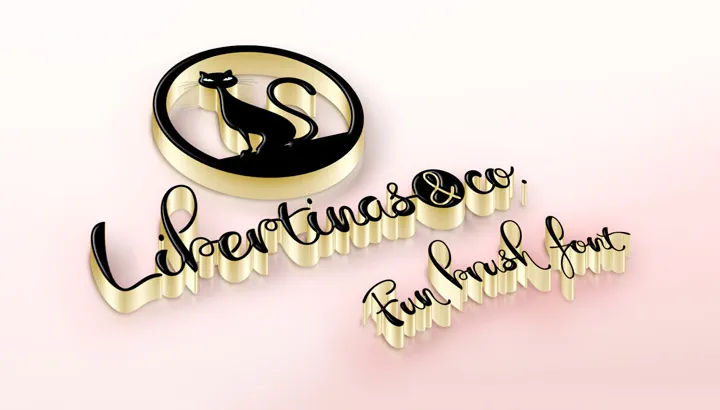
A Libertinas & co. Font é uma tipografia feita à mão que traz um estilo casual, elegante e sensual, com muitas possibilidades para compor títulos, panfletos ou até mesmo postais de design gráfico. Com seu charme próprio, essa fonte criativa oferece inúmeras oportunidades para personalizar textos de forma única e envolvente. Para designers que apreciam um toque autêntico em suas criações, a Libertinas & co. é uma opção ideal para tornar seus projetos ainda mais singulares e únicos. Seja para uso em editoriais, websites ou impressões, essa fonte escrita à mão do designer defharo oferece inúmeros recursos que podem ser explorados. Não deixe de experimentar a Libertinas & co., uma adição maravilhosa ao seu kit de ferramentas de design.